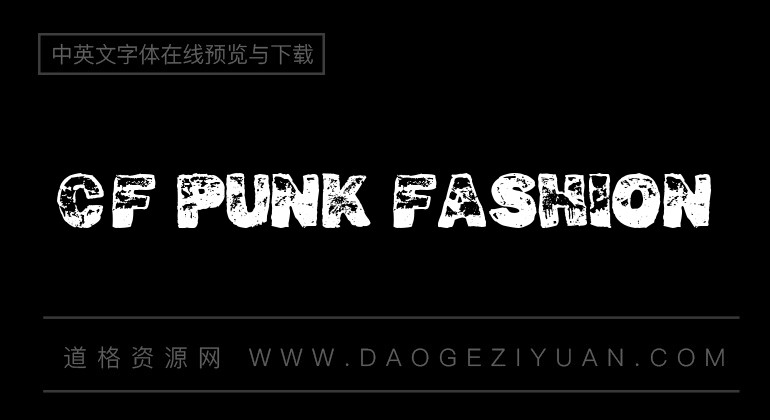
CF Punk Fashion
CF Punk Fashion字体是一款抽象灵感来自于摇滚乐的字体,它的外观充满了激情和力量,令人难以忘怀。它的字体风格比较粗犷,充满了朋克风格的活力,而且它的字体特征也更加具有个性,能够更好地表达出朋克文化的精神。它的字体设计也更加现代化,能够更好地满足现代人的需求。
CF Punk Fashion是一款非常不错的手写艺术字体,具有很好的视觉感,适合于文化类的宣传设计、商业类品牌的广告和产品包装设计以及个性化文字排版等较多场景。